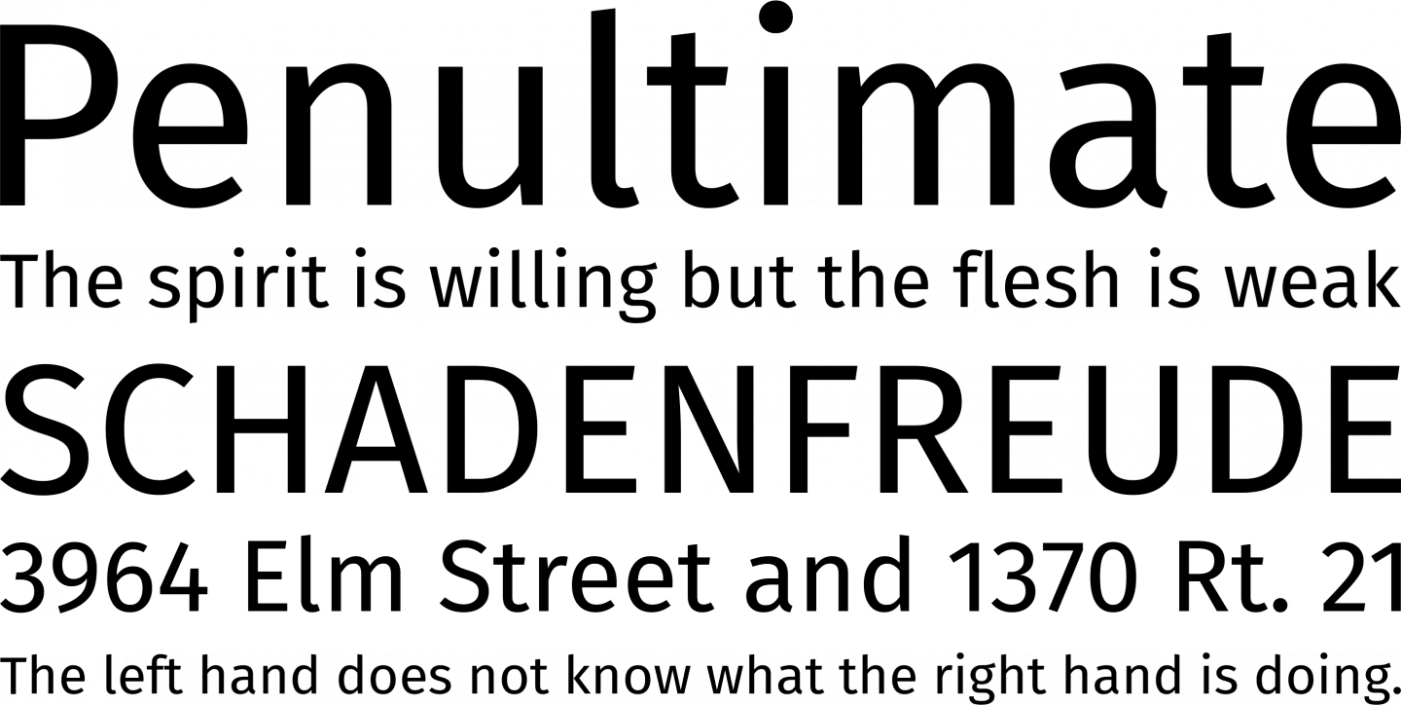
Font mit chinesischer Sprachunterstützung als Alternative zur Fira Sans
für die Übersetzung einer Broschüre suche ich ein Pendant zur Fira Sans mit chinesischer Sprachunterstützung.
Könnt Ihr mir dazu eine Font-Familie empfehlen? Die Fira Go von bBox Type wird ja momentan zu einer global funktionierenden Schriftfamilie ausgebaut. Allerdings hat sie bedauerlicherweise noch keinen chinesischen Zeichensatz im Repertoire, wenn ich das richtig sehe. Sonst wäre sie natürlich die erste Wahl.
Ich würde die Fira mit einem chinesischen Font mischen. Da die chinesichen Zeichen ihren quadratischen Grundriss idealerweise nicht verlassen, kämst du mit "irgendeiner" Hei (vulgo: "Sans") zurecht. Wenn du magst, kannst du dir aber auch diese drei Seiten Hei-Stil-Varianten* anschauen. Welche von denen zur Fira für dich/deinen Kunden am besten passt, kannst du für dich selbst entscheiden; es gibt da keine "Regel". So eine Übersicht gibt's natürlich auch von Hanyi.
Ich würde die Fira mit einem chinesischen Font mischen.
Machen wir auch immer so, Zahlen und lateinische Buchstaben ersetzen wir immer. Sieht sonst ziemlich gruselig aus Bei Messen steht Chinesisch und Englisch immer untereinander, da fällt es also deutlich auf.